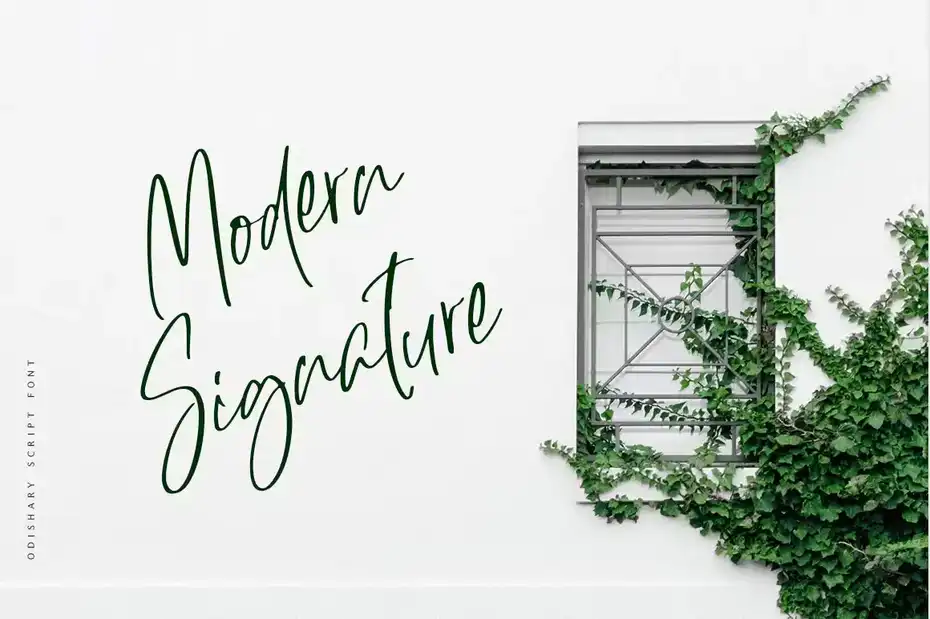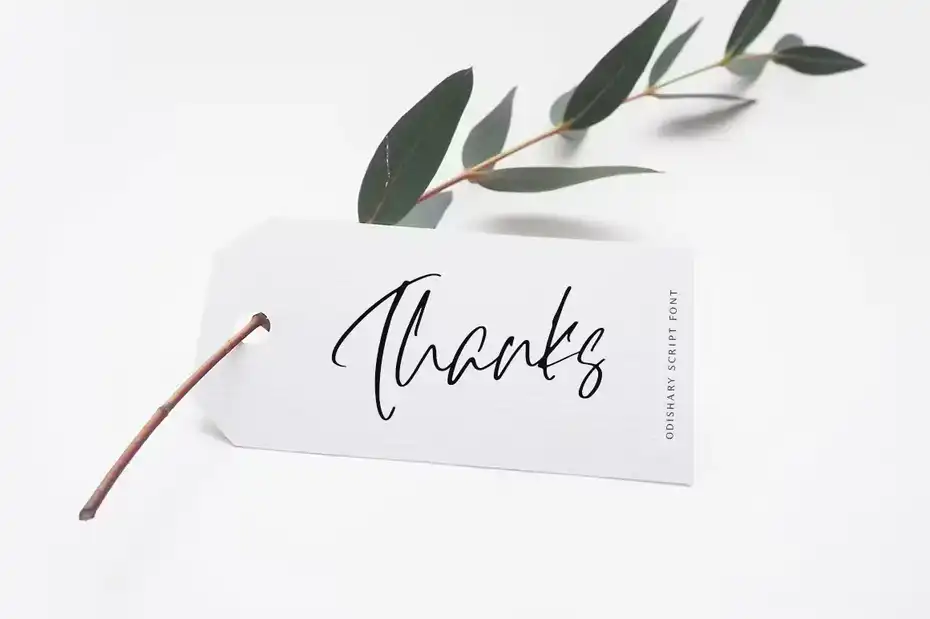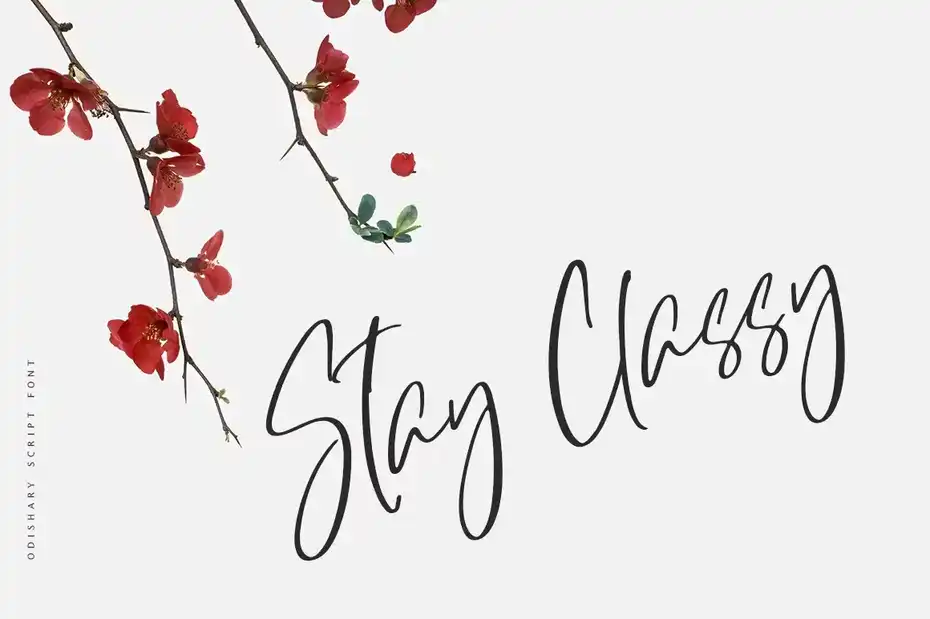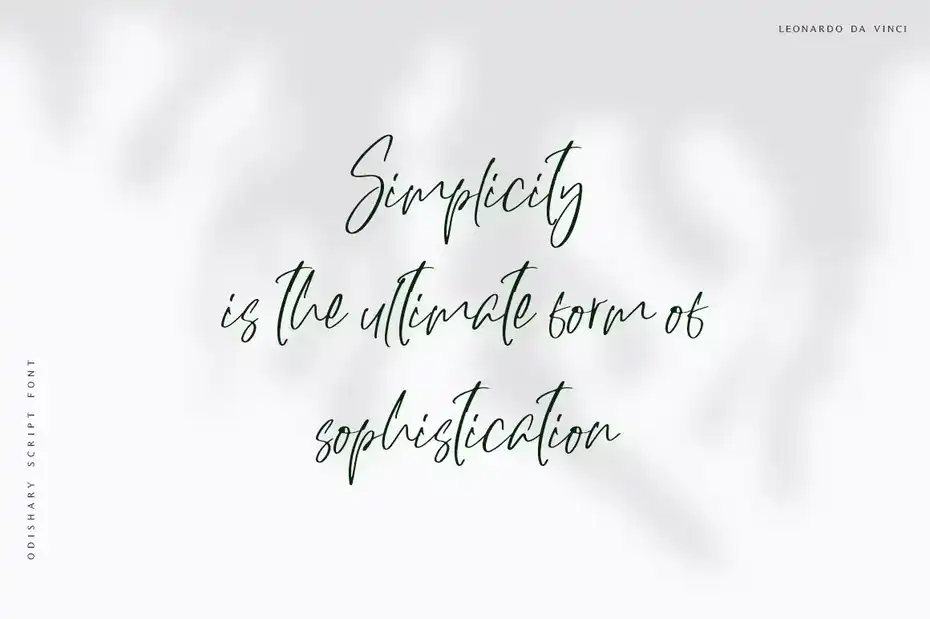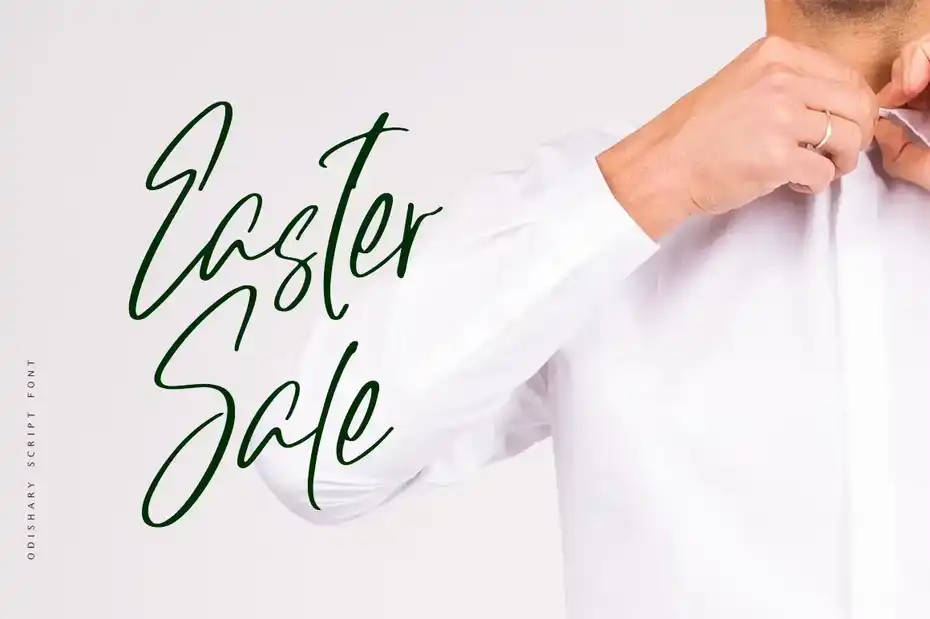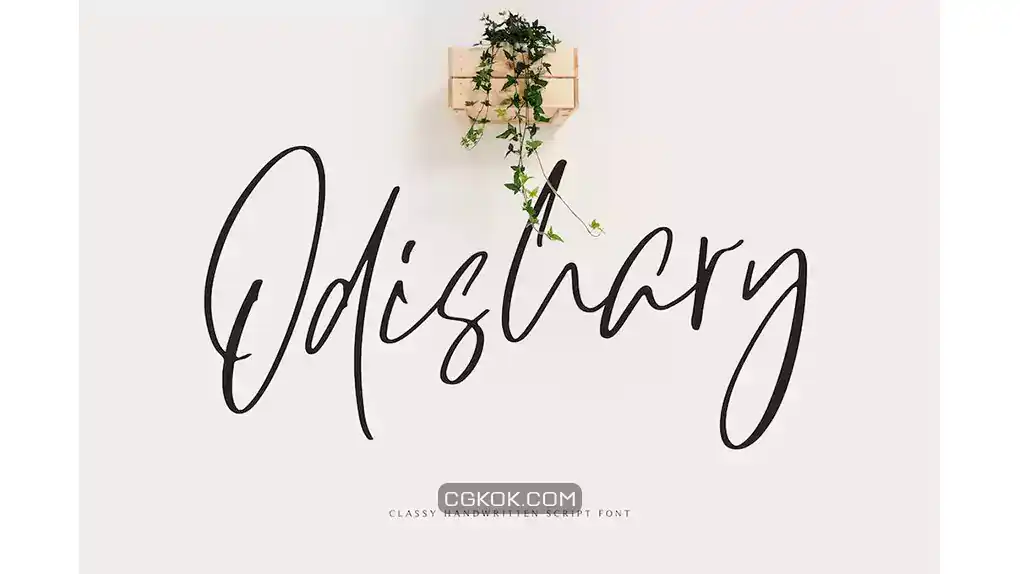
دانلود فونت انگلیسی پیوسته Odishary – Handwritten Font
فونت انگلیسی پیوسته Odishary – Handwritten Font : این مجموعه شامل فونت انگلیسی دست نویس است که برای امضا، لوگو، برندینگ، کارت دعوت عروسی، نقل قول، پوستر، فیلم و غیره مناسب میباشد.
فونت انگلیسی پیوسته Odishary - Handwritten Font - 1
فونت انگلیسی پیوسته Odishary - Handwritten Font - 3
فونت انگلیسی پیوسته Odishary - Handwritten Font - 5
فونت انگلیسی پیوسته Odishary - Handwritten Font - 7
فونت انگلیسی پیوسته Odishary - Handwritten Font - 9